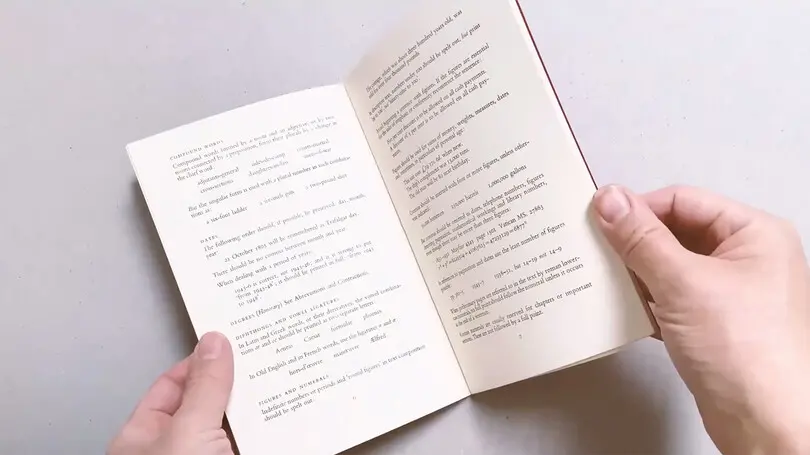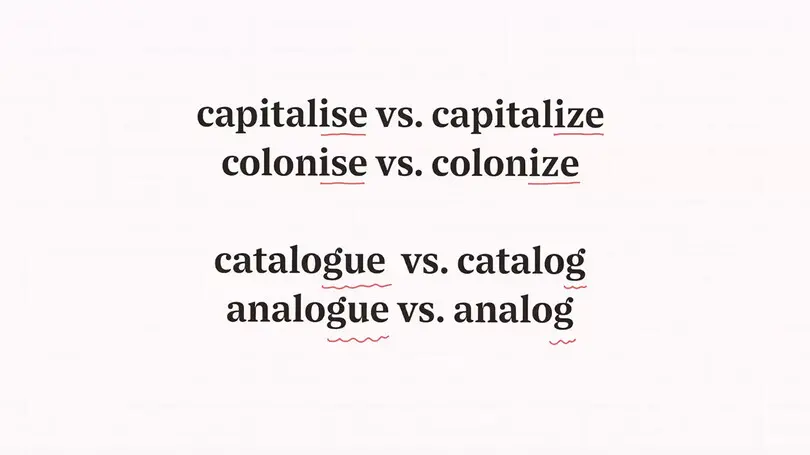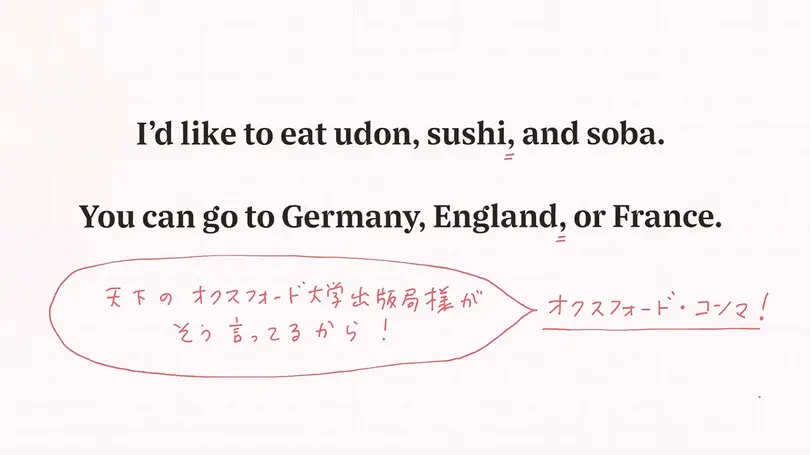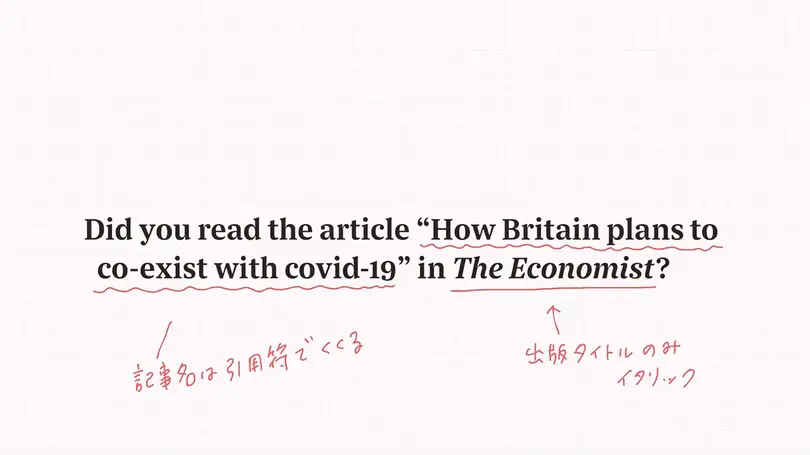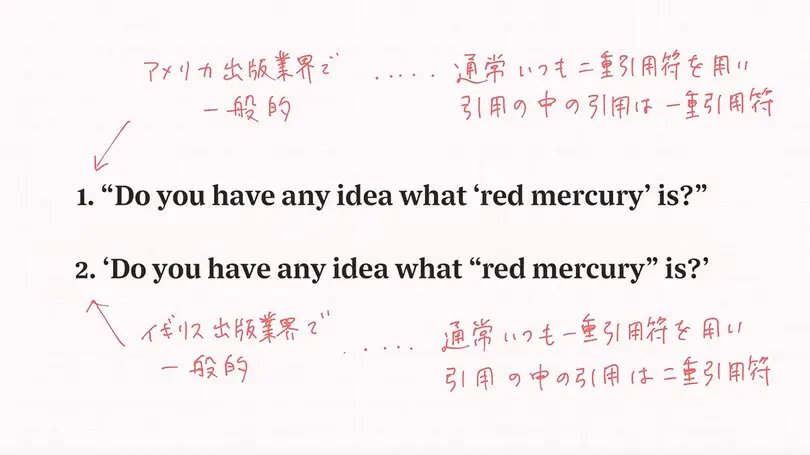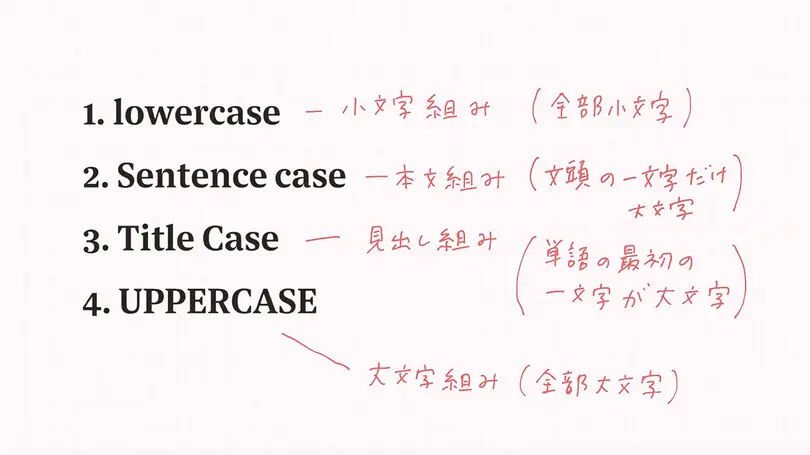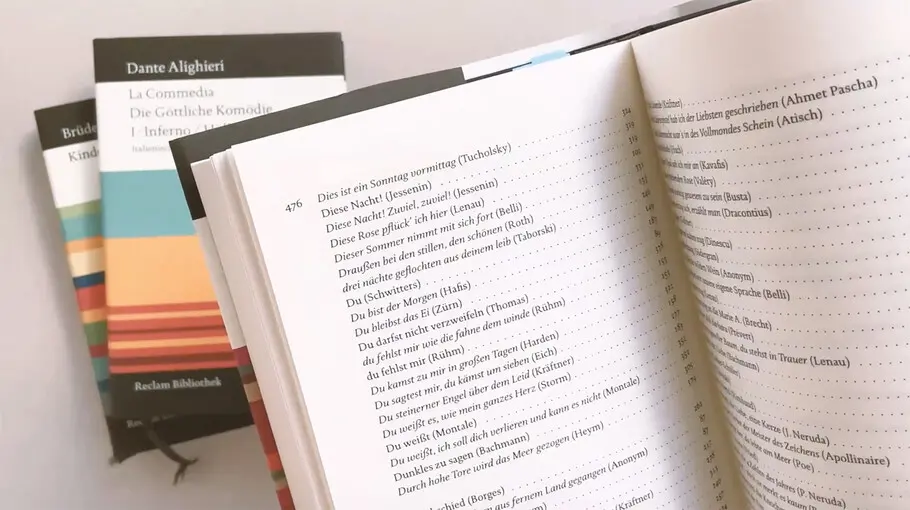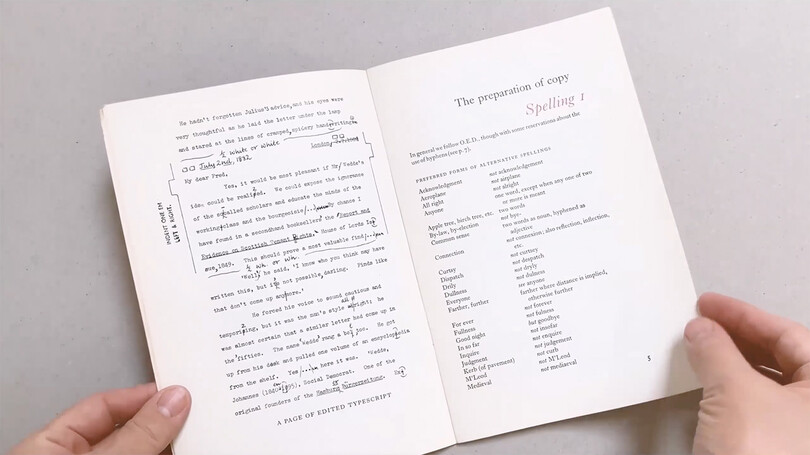
欧文組版の醍醐味とハウス・スタイルについて
麥倉聖子(むぎくら・しょうこ)氏のプレゼンテーション。麥倉氏は武蔵野美術大学卒業後、イギリスのレディング大学で欧文タイポグラフィを学び、ロンドンのデザイン事務所に勤務。現在はドイツのミュンヘンでティム・アーレンス氏とタイプファンダリー「Just Another Foundry」(以下、JAF)を運営し、書体開発や欧文組版の仕事をされています。
マクロ・タイポグラフィとマイクロ・タイポグラフィ
2020年のType&では「コーポレートフォントの運用、欧文組版のミスの種類を分析・解説」というタイトルで、コーポレートフォントを運用する際の問題点や、よくあるミスについて、その原因や対応方法について解説されました。
2021年のType&では、最初に「マクロ・タイポグラフィ」と「マイクロ・タイポグラフィ」についての説明がありました。マクロ・タイポグラフィとは、レイアウトやグリッド、組版形式など、一般の人が見てもわかる組版の大きな枠組みのことです。一方、マイクロ・タイポグラフィとは、行間や文字間のスペーシング調整、ハイフンの設定や文末調整、組版ルールや表記法の統一など、地味で時間のかかる組版の細かな調整を指します。
マクロ・タイポグラフィは、ある程度、見た目や感覚で判断して実践できるのに対して、マイクロ・タイポグラフィは、使われる文字や言語、組版ルールの知識を必要とするので、手間がかかると思われがちです。しかし、マイクロ・タイポグラフィにこそ欧文組版の醍醐味があります。白黒だけで情報を正確にわかりやすく、統一性を持たせエレガントに提示する方法を、活版印刷の発明以来、何百年もかけて考えてきた先人たちの知恵が詰まっていると麥倉氏は言います。
ハウス・スタイル/ハウス・ルールとは?
今回のType&では、マイクロ・タイポグラフィの中でも組版ルールや表記法に焦点を当て、表記と組版の決まりごとをまとめた「ハウス・スタイル/ハウス・ルール」が紹介されました。「ハウス」というのは「うちの、我が家の」という意味で、組織で出版物や広報物を作る時、特別な理由がない限りそのルールに従って作るという決まりごとを「ハウス・スタイル(=我が家の様式)」「ハウス・ルール(=我が家のルール)」と言います。
ハウス・スタイルは、DTP以前の英語圏では一般的で、いろいろな印刷会社、出版社、大学出版局、美術館などがハウス・スタイルをまとめた冊子を作っていました。これらの冊子には英語を組む際に必ず考えなくてはならない点が単純明快に書かれており、クライアント、デザイナー、組版者がそれらを共有することで、ミスを防ぐことができるのです。今回のType&では、ハウス・スタイルの冊子を見せながら、いろいろな組版ルールの説明が行われました。
ハウス・スタイルの冊子紹介
House style
イギリスの出版社、ジョナサンケイプのハウス・スタイル。9章28ページの超コンパクトな冊子だが、中の組版もよい。章タイトルが赤で大きく組まれ、探している情報も探しやすい。
Authors’ guide: an introduction to the Tate Gallery style manual
ロンドンのテートギャラリーのスタイル・ガイド。文章を書く人、準備する人向けだが、組版をする人にとっても興味深い内容。
Style of the house
London College of Printing(現在はLondon College of Communication)という有名な美術大学のハウス・スタイル本。32ページ。生徒用なので、かなり単純明快に書かれている。
House style
出版元:North-East Essex Technical College and School of Art
イーストエセックス美術大学のハウス・スタイル本。美術大学や附属の印刷部門が積極的にハウス・スタイルを出版していて、印刷業界と応用美術が本当に密着していることが感じられる。
Style of the house
出版元:James Upton Ltd, and its Associated Company, Surrey Fine Art Press Ltd
印刷会社のハウス・スタイル本。チラシやステーショナリーを扱う会社のようで、住所の組版など具体的な例が紹介されている。書籍では編集者や校正者のチェックが入るが、チラシなどの簡単な制作プロセスで世の中に出るものほど、原稿を用意する最初の段階でミスを避けられると効率的。
Printing style for authors, compositors and readers
出版元:George Allen & Unwin Ltd
経験豊かな校正者が読者に語りかけるように書かれた100ページほどの本で、Plantinという書体で組まれている。文字を組んだ時のテクスチャーと読みやすさが最高。
いろいろな冊子を見たあと、具体的なポイントに絞って解説されました。
スペリング
どのハウス・スタイルにも必ず登場するのが、スペリングの一貫性についてです。例えば、SEで終わるのか、ZEで終わるのか、複数のスペリングの様式が存在する場合、どちらに統一するのかが必ず書かれています。
句読点
また、句読点についても必ず書かれています。この中でも厄介なのは句点ではなくて読点、コンマです。「コンマは必要最低限だけ使いましょう」「使い方に統一性を持たせましょう」とどのハウス・スタイルにも書かれています。
例えば、「ドイツか、イギリスか、フランスに行く」など、いくつかの物を並列させる英文で、andやorの前にコンマを入れるかどうか、ハウス・スタイルに必ず書かれています。このような3つ以上のことがらの並列の前に入れるコンマは「オクスフォード・コンマ」と呼ばれ、イギリスでの表記法の権威であるオクスフォード大学出版局が「andやorの前にコンマを入れるのが正しい」と決めているため、そのように呼ばれています。しかし、実際にはこのオクスフォード・コンマを入れないハウス・スタイルの方が多いそうです。
これらの例は、現地の人は学校で習うので、知識として知っていることが多いそうですが、ネイティブではない外国人が欧文組版をする場合は意識しないと抜けてしまう注意ポイントであると麥倉氏は言います。
イタリック
ハウス・スタイルにはタイポグラファの責任領域である組版ルールも記載されています。例えば、どこでイタリックを使うのかなどです。「Did you read The Economist?(『エコノミスト』誌を読みましたか?」という英文では、雑誌名の『The Economist』の部分がイタリックになります。
一方、「Did you read the article “How Britain plans to co-exist with covid-19” in The Economist?(『エコノミスト』誌に掲載されていた「イギリスはコロナとどう共存するのか?」という記事を読みましたか?」)という英文では、雑誌名のみイタリックで、記事のタイトルは引用符で囲みます。
引用符
引用符は英語で、「Quotation(クォーテーション)」とか「Quotation Mark(クォーテーション・マーク)」と呼びます。アメリカとイギリスで引用符の使い方が異なり、図の1はアメリカ、2はイギリスの出版業界のスタイルになります。アメリカ英語とイギリス英語では発音が違いますが、表記上のルールも相違点があります。
大文字の使い方
英語では大文字のことを「Capital(キャピタル)」と呼び、どこで大文字を使うかは英語組版の難しい点です。
ドイツ語のタイトルでは、名詞の最初の一文字だけ大文字で、形容詞や動詞は小文字という組み方と、全部大文字という二択しかなく、文章中では図の1以外の選択肢はありません。
ところが、同じ本のタイトルを英語で組む場合、基本的には4種類の組み方があります。
1. ローワーケース。すべて小文字
2. センテンスケース。文の最初だけ大文字
3. タイトルケース。単語の最初だけ大文字
4. アッパーケース。全部大文字
1の全部小文字と4の全部大文字は、ビジュアル効果を狙った特別な時にしか使いませんが、難しいのが選択肢2と3です。例えば、ある文章中に本や映画のタイトルが出てきた時に、2のセンテンスケースなのか、3のタイトルケースなのかを統一する必要があります。そして、3を選んだ場合は、代名詞、前置詞、副詞をどうするのか悩むと麥倉氏は言います。
一つの仕事の中で統一しようとしても、タイトルによっては変に見えたり、一貫性がなく見えたりするので、英語組版の大文字の使い方は非常に難しいそうです。デザインがよくても、大文字小文字の使い方に一貫性がなければ、だらしない印象を与えてしまう可能性があるとのことでした。
今回の講演では、イギリスの活字時代に存在したハウス・スタイル本を紹介しながら、欧文組版の踏み込んだ話を解説していただきました。麥倉氏は、現地で欧文組版について学び、実践していくうちに、欧文組版は見た目がエレガントなだけではなく、非常に機能的であると感じたそうです。活版印刷時代のよくできた本を見ていると、完全に白黒で、書体サイズも多くても2種類しか使わずに、大文字、イタリック、スモールキャップ、最小限の約物とスペーシングを駆使して、文章の構造を視覚的に伝わりやすくしています。それらを見ると、「これこそ欧文組版の醍醐味」と感動してしまうそうです。
よい欧文組版の本を見つけるコツ
組版の良し悪しを判断するならば、表紙や本文ページではなく、参考文献や解説ページをチェックするとよいと麥倉氏は言います。本の後ろのページは、本文ページよりテキストの構成が複雑で、組版の技術がより必要になるからだそうです。作業にも時間がかかるため、組版に愛がある人以外は適当に組むこともあるそうです。しかし、こういうページがきちんと組版されていたら、その本の組版のクオリティは保証付きです。麥倉氏は、目次ページ、参考文献、索引ページを必ずチェックするとのことでした。